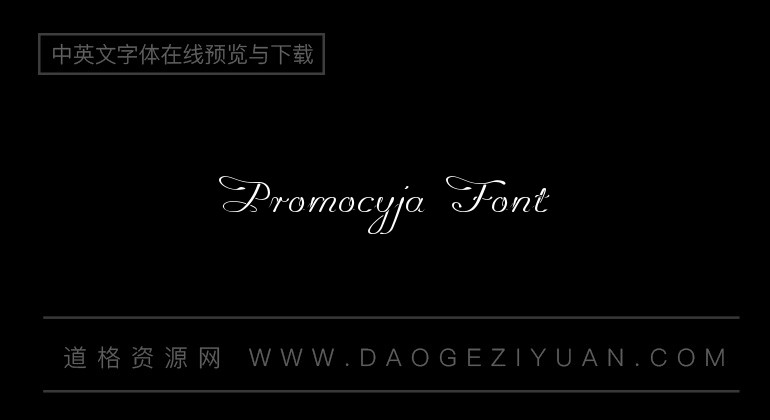
Promocyja Font是一种手写风格的字体,由Tomasz Ludzinski于2014年设计。该字体的风格简洁明快,给人一种自然的感觉,同时保留了手写的特点,具有很好的可读性。 Promocyja Font字体包括大写字母、小写字母、数字、标点符号和一些特殊字符。该字体适用于各种设计项目,如海报、传单、书籍、网站和标志等。 该字体还有不同的重量,从正常到粗体,让设计者可以根据自己的需要自由选择。此外,Promocyja Font字体还支持多种语言,包括英语、法语、德语、意大利语、西班牙语等。 总体而言,Promocyja Font是一种具有独特风格的手写字体,适用于各种设计项目,带来自然、简洁、可读的效果。内容介绍
Promocyja Font是一款非常不错的手写艺术字体,具有很好的视觉感,适合于文化类的宣传设计、商业类品牌的广告和产品包装设计以及个性化文字排版等较多场景。